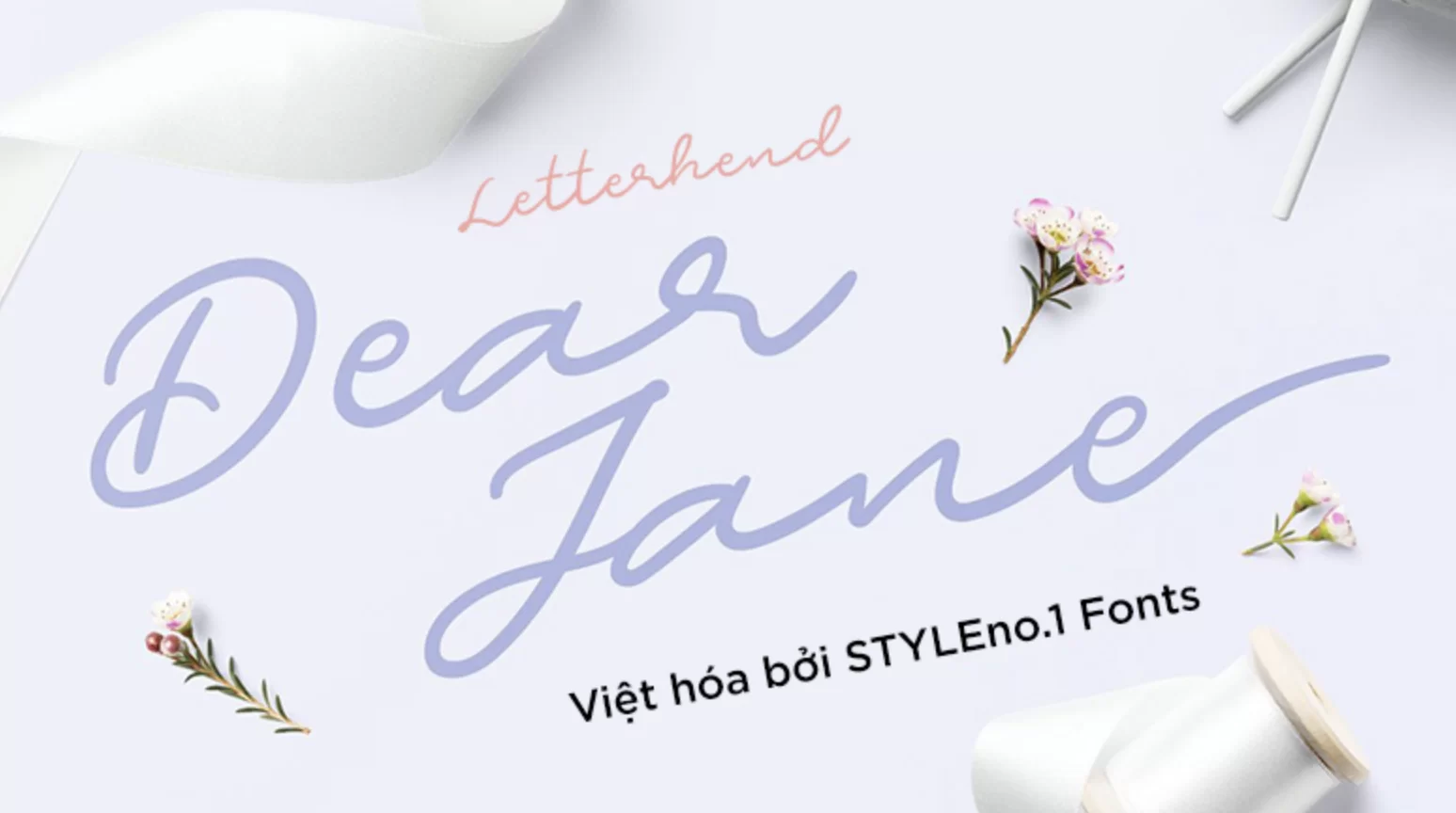
Kiểu chữ đáng yêu này được làm từ các nét vẽ viết tay nhằm tạo cảm giác tự nhiên và lãng mạn. Hoàn hảo để được sử dụng đặc biệt cho chữ ký, thiệp cưới, thiệp chúc mừng, logo, nhiếp ảnh, thiết kế trang phục và bất kỳ nhu cầu thiết kế nào. Như thường lệ, phông chữ đi kèm với nhiều tính năng opentype như chữ ghép, bộ thay thế phong cách, vv và cũng hỗ trợ đa ngôn ngữ.
Nhà thiết kế: Letterhend
Việt hóa: STYLEno.1 Fonts